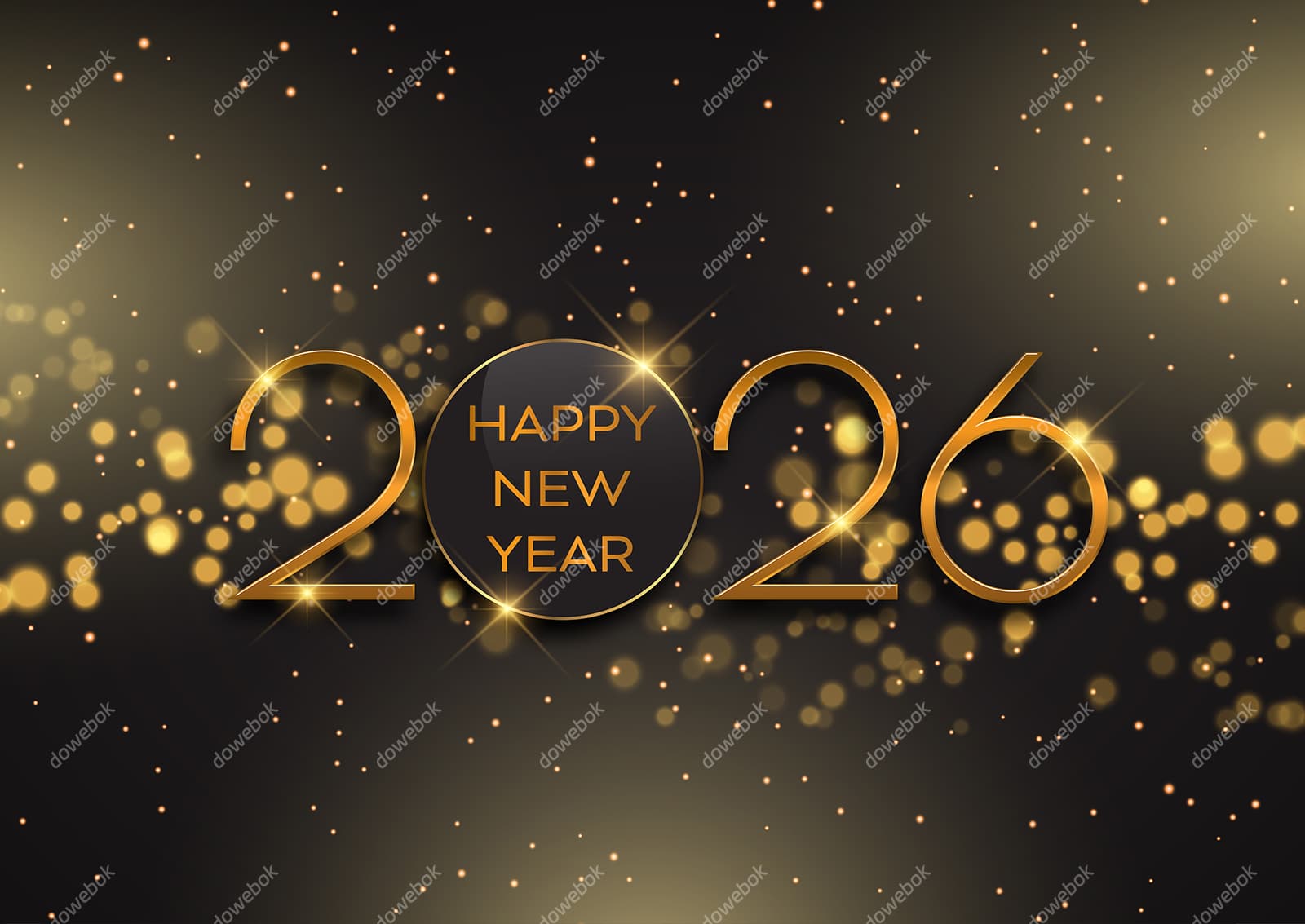
这是一款金色星点和金色数字设计 2026 新年快乐矢量素材,深黑背景散落金光斑与星点,营造轻奢柔美的氛围。金色线条勾勒出 “2026” 字体,数字间嵌入圆形标牌,印着 “Happy New Year” 字样,标牌边缘闪着星光亮点。整体以黑金配色 + 柔和光晕,既显精致高级,又透出跨年的温馨与仪式感,简约中藏着节日的雅致。